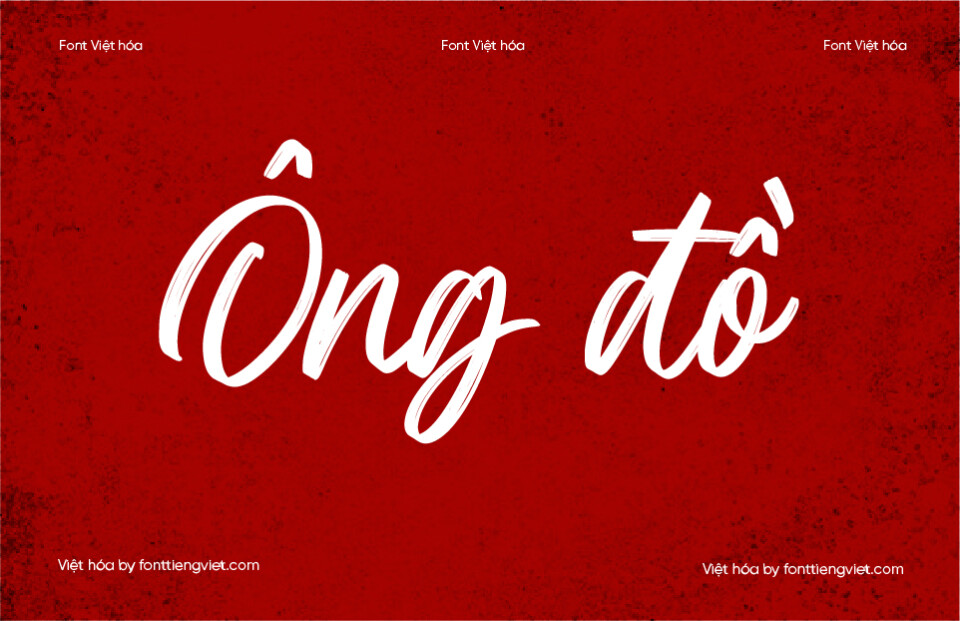
Font Việt hóa 1FTV VIP Hesmony – Brush: Lựa chọn hoàn hảo cho thiết kế năng động
Giới thiệu về Font Việt hóa 1FTV VIP Hesmony – Brush
Trong thế giới thiết kế đồ họa hiện đại, việc tìm kiếm một bộ Font Chữ mang đậm cá tính riêng biệt là điều vô cùng quan trọng đối với các bạn học sinh và giáo viên. Font Việt hóa 1FTV VIP Hesmony – Brush nổi lên như một giải pháp tuyệt vời nhờ phong cách viết tay phóng khoáng và mạnh mẽ. Đây là bộ phông chữ thuộc dòng Brush (cọ vẽ), mang lại cảm giác thủ công tự nhiên nhưng vẫn giữ được sự tinh tế và chuyên nghiệp cần thiết cho các dự án học tập hay truyền thông tại nhà trường.
Đặc điểm nổi bật của Hesmony Brush
Bộ phông chữ này sở hữu những đường nét uốn lượn sắc sảo, tạo hiệu ứng thị giác mạnh mẽ ngay từ cái nhìn đầu tiên. Điểm đặc biệt của Font Việt hóa 1FTV VIP Hesmony – Brush chính là khả năng hiển thị tiếng Việt hoàn hảo, không bị lỗi dấu, giúp người dùng dễ dàng ứng dụng vào việc làm báo tường, thiết kế slide bài giảng hoặc trang trí các ấn phẩm sự kiện. Sự kết hợp giữa nét thanh và nét đậm giả lập cọ vẽ giúp các tiêu đề trở nên sống động và có chiều sâu hơn rất nhiều so với các phông chữ truyền thống.
Ứng dụng thực tế của Font Việt hóa 1FTV VIP Hesmony – Brush
Sáng tạo trong môi trường giáo dục
Học sinh có thể sử dụng bộ chữ này để thiết kế bìa tiểu luận hoặc làm video thuyết trình thêm phần lôi cuốn. Trong khi đó, thầy cô có thể dùng nó để tạo ra các tấm thiệp khen thưởng đầy cảm hứng. Sự linh hoạt của Hesmony giúp mọi thông điệp trở nên gần gũi và thân thiện hơn. Hy vọng rằng với Font Miễn Phí, Font Việt Hóa, Font Việt hóa 1FTV VIP Hesmony – Brush, các bạn sẽ có thêm nhiều ý tưởng sáng tạo độc đáo. Hãy tải ngay để trải nghiệm sự khác biệt mà bộ chữ này mang lại cho tác phẩm của bạn.